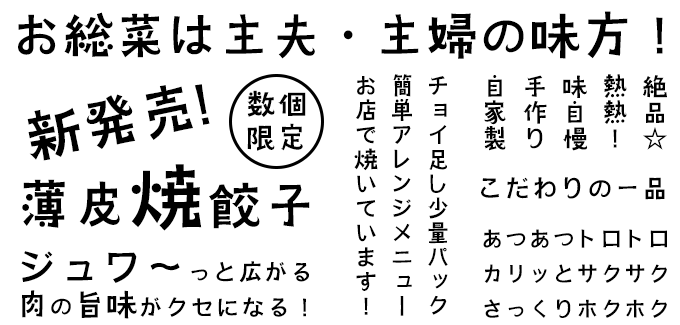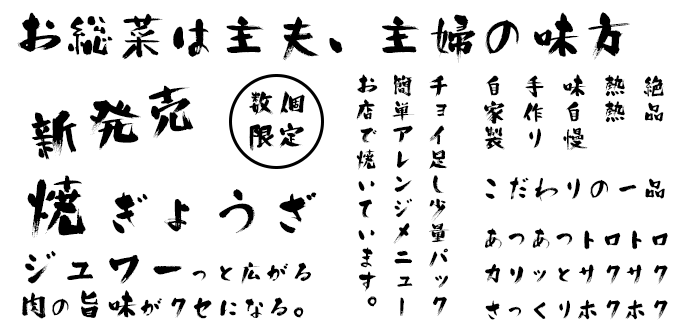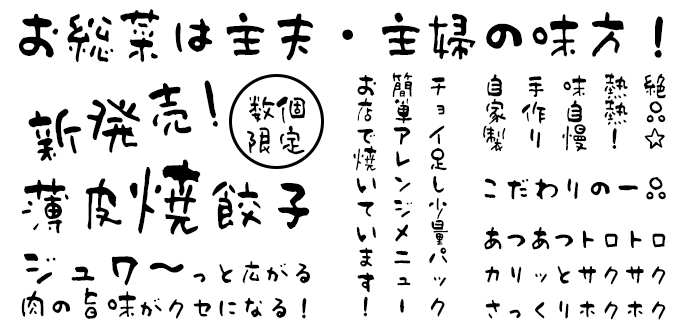
お惣菜POPに合うフォント 特化型 目的別フォントガイド
お惣菜POPに合うフォント:特化型 目的別フォントガイド #022
今回はお惣菜POPに合うフォント。日々フォントのことばかり考えている当店スタッフが直感的に選んだフォントをご紹介します。
お惣菜POPに合うフォントをスタッフが選びました
お惣菜POPに合うフォント #1 花とちょうちょ
花とちょうちょ【鈴木メモ】
一般社団法人全国スーパーマーケット協会主催の「お弁当・お惣菜大賞2020」でオリジナル商品7品がランクインした、お惣菜、PBに力を入れているスーパーでも使用されているフォント。
お惣菜POPに合うフォント #2 遊妖体 (ゆうようたい Std・StdN同梱)
遊妖体 (ゆうようたい Std・StdN同梱) 【楽フォント】
遊び心溢れる文字でお惣菜パッケージに入れると楽しい食事時間が想像できるような文字だと思い、選びました。サラダのパッケージにも、揚げ物のパッケージにも似合いそう。
お惣菜POPに合うフォント #3 ARマーカー体E
ARマーカー体E【アーフィック】
フェルトペンで書いたタッチの書体です。手作りの惣菜にピッタリな、手書きの優しい雰囲気が伝わるPOPを作ることが出来ます。
お惣菜POPに合うフォント #4 バサころ書体
バサころ書体【昭和書体/コーエーサインワークス】
バサころは力強い筆文字ながらも、かすれが柔らかさをかもし出しているデザインです。”はらい”も太いので英数字の表記にも違和感がありません。
お惣菜POPに合うフォント #5 ARハイカラPOP体H
ARハイカラPOP体H【アーフィック】
ちょっと古めかしいデザインにも見える、不思議なポップ書体。縦線に比べて横線が若干補足、角ペンマーカーで書いたようなPOPを作ることが出来ます。
お惣菜POPに合うフォント #6 AR古印体B
AR古印体B【アーフィック】
昔から使用されている印影をイメージした書体。本来は印鑑向けですがホラー作品にもよく使われている為、POPに使うと「なんでこの書体を選んだの?」とツイッターでバズります。
お惣菜POPに合うフォント #7 DFスティック W5
DFスティック W5【ダイナフォント】
楷書の骨組みにどっしりとした筆画を組みわせ、隷書の特徴である右上に軽く突き上げるような筆画を取り入れたデザイン。見やすく目を引きます。
お惣菜POPに合うフォント #8 DF POPコン W12
DF POPコン W12【ダイナフォント】
マーカーで手書きしたようなデザインの書体。字のバランスが左右対称で細い横画と太い縦画に遊び心のある点筆を組みわせることにより、親しみやすさをプラス、惣菜POPらしい書体です。
お惣菜POPに合うフォント #9 DF唐風隷書体 W5
DF唐風隷書体 W5【ダイナフォント】
横長で太く扁平な字形がどっしりと落ち着きを感じさせる隷書体。中華料理などのお惣菜にピッタリの書体です。
お惣菜POPに合うフォント #10 話話体
話話体【楽フォント】
2021年9月発売の新書体。インパクトのあるエレメントでテンポの良さを字形に実現しています。他と差をつけたいならマストバイです。
お惣菜POPに合うフォント #11 黒龍書体
黒龍書体【昭和書体/コーエーサインワークス】
太細差のある筆書系デザイン書体は、力強いイメージを感じさせるので「熱熱」や「コク旨」など味覚を表現する時にピッタリだと思います。
お惣菜POPに合うフォント #12 髭筆フォントシリーズ 爆天書体-旺-
髭筆フォントシリーズ 爆天書体-旺-【Design筆文字Font】
豪快な筆致でありながら、温もりと優しさを有した人情味ある書体。揚げ物などの惣菜POPにぴったりのフォントです。
お惣菜POPに合うフォント #13 デザイン筆文字フォント酔虎
デザイン筆文字フォント酔虎【マール社】
筆文字風の擦れが和のテイストにピッタリ。お刺身、焼き魚、煮物など和食コーナーで映えるフォント。